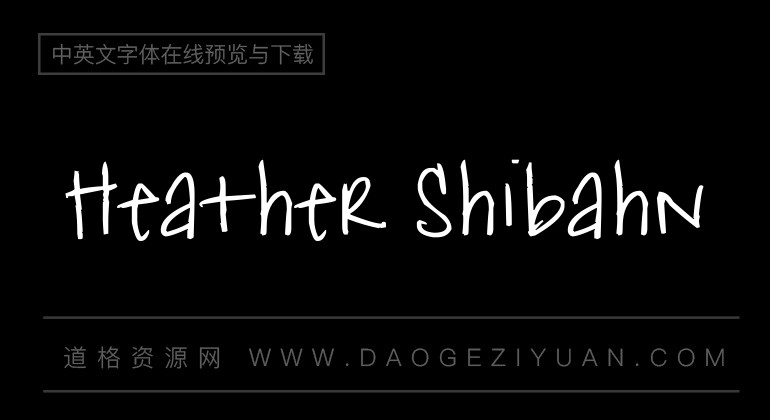
Heather Shibahn
Heather Shibahn字体是一款具有清新可爱风格的手写字体,它具有温柔的质感,而且具有柔和的曲线,给人一种温暖的感觉。它的字符拥有完美的结构,让文字看起来更加精致,给读者以深深的印象。它可以用于印刷、网页设计、广告宣传物料、礼品包装等等。
Heather Shibahn是一款非常不错的手写艺术字体,具有很好的视觉感,适合于文化类的宣传设计、商业类品牌的广告和产品包装设计以及个性化文字排版等较多场景。
Heather Shibahn字符映射图